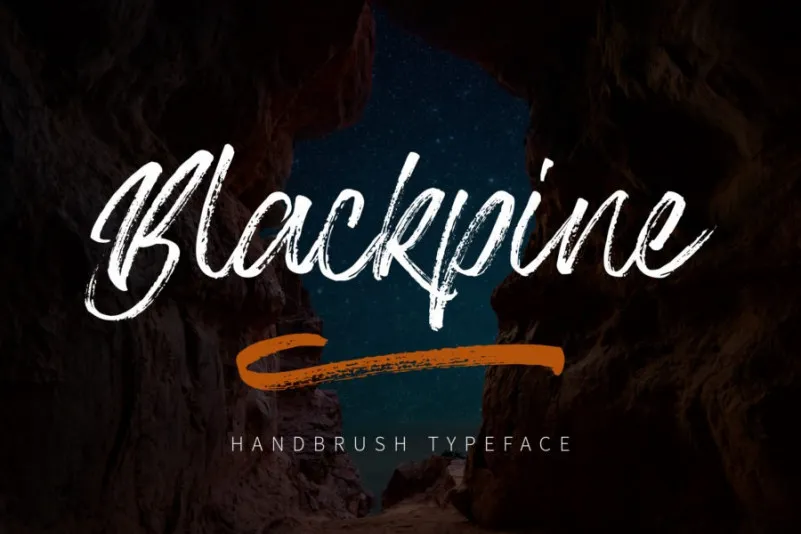
Blackpine Brush Font
A Blackpine Brush Font é uma fonte feita à mão que apresenta traços delicados de tinta e desenhos, criando caracteres impressionantes. Com um visual elegante e sofisticado, esta fonte encaixa-se perfeitamente em projetos variados como moda, roupas, assinaturas, capas de álbum, logotipos, marca, revistas e mídias sociais, além de anúncios. Ela é uma opção ideal para quem procura um toque único e sofisticado que pode complementar qualquer projeto gráfico. Sempre lembre-se de testá-la em diferentes tamanhos e contextos antes de integrá-la em seus trabalhos finais, pois a experiência real pode variar ligeiramente conforme o dispositivo ou sistema operacional utilizado.